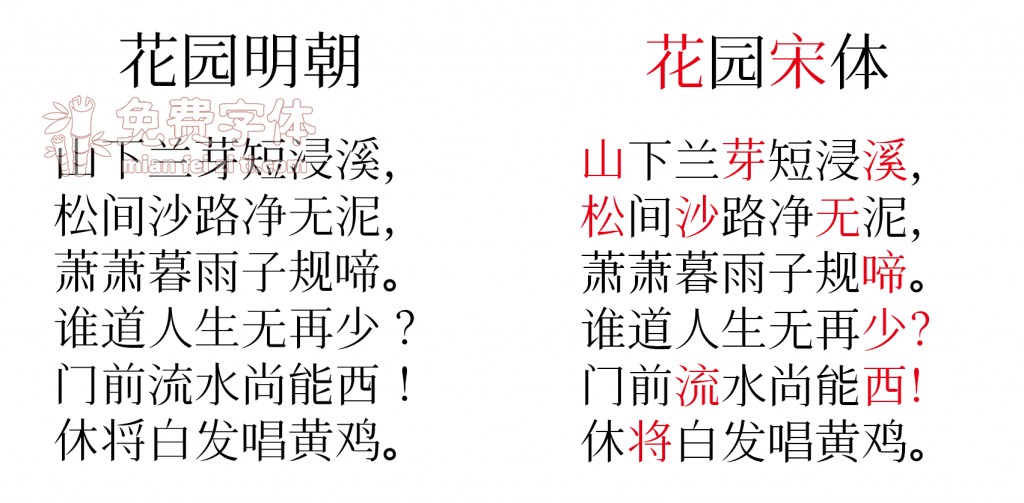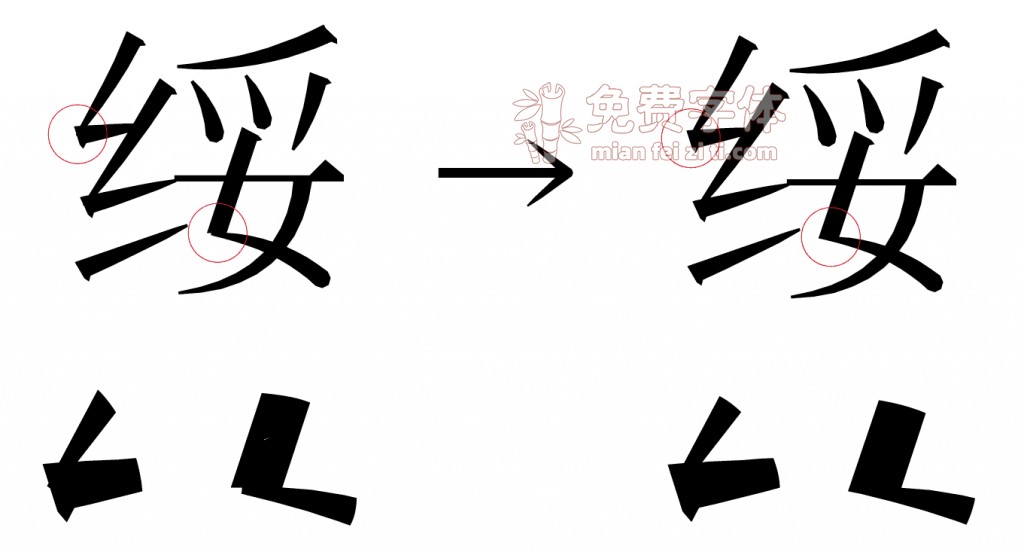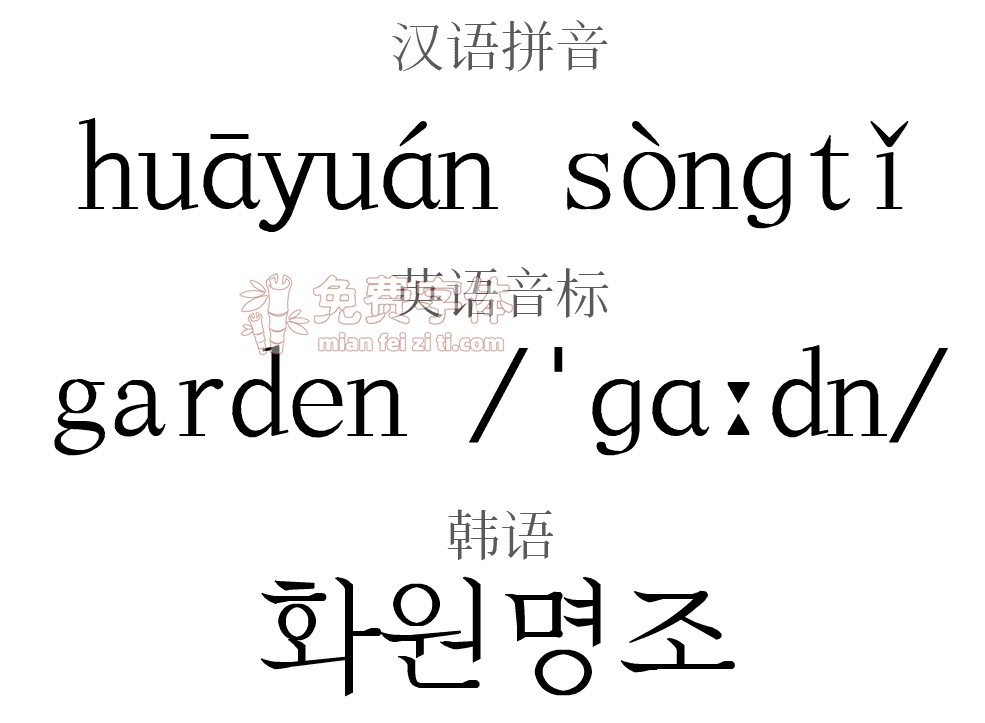
花园明朝 (Hanazono) 是一款免费字体,为GlyphWiki(字形wiki)所开发,几乎收录了所有汉字字形。缺点是字形以日本字形为准,有一些字不符合中文书写规范(不论是大陆规范还是港台规范)。在我了解到了字形wiki这个网站后,我决定将花园明朝体改成适合我们大陆人实用的版本,命名为“花园宋体”。
花园宋体收录大陆简体(GB2312-80)的6763个汉字,其余汉字不收入。此外删去了多余的语言文字,加入了韩文字符11292个。
其中,部分汉字的大陆字形并未制作,我也使用kage editor(HTML5)进行了创作,也为字形Wiki献了一份力。
在折笔处kage editor制作的效果不佳,对此进行更改,效果如下: